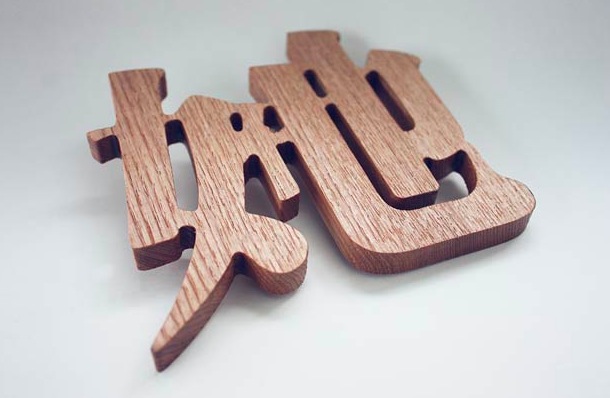
Asiatische Schriftarten haben für mich immer etwas sehr Ästhetisches und irgendwie Beruhigendes. Ich finde man spürt förmlich die lange Tradition der Schriftkunst in den perfekt geschwungenen Linien und Zeichen. Ganz besonders beeindruckend sind natürlich die sehr komplexen chinesischen Schriftzeichen, die auf chinesisch „hànzì“ genannt werden. Bei so viel Schrifttradition und einer Schrift, die aus mehreren tausend Zeichen besteht, ist es natürlich ganz besonders spannend zu beobachten, wie moderne Typografen und Designer die Schriftzeichen in ihren modernen Arbeiten interpretieren.
Die chinesische Kunst- und Designszene stand längere Zeit im Schatten der sehr viel moderneren Designarbeiten aus Japan oder Korea. Doch in den letzten Jahren hat sich einiges getan und in den chinesischen Megacities gibt es heute eine lebendige Szene junger Künstler und Designer. Da es immer wieder spannend ist, sich von Design und Kunst aus anderen Kulturkreisen inspirieren zu lassen, habe ich hier einige typografische Arbeiten aus China zusammen gestellt.
Plakatkunst
Dieses typografische Plakat hat der sehr erfolgreicher junger Grafikdesigner Qian Qian gestaltet. Mir gefällt besonders die Kombination aus modernem, minimalistischem Design und den traditionellen, wie ein Holzschnitt wirkenden Muster. Weitere Arbeiten des Künstlers kannst du dir auch auf seiner Webseite www.q2design.com anschauen.
Piktogramme
Die Piktogramme wurden alle nach bekannten Schriftzeichen, Figuren aus bekannten chinesischen Sagen oder Sprichwörtern gestaltet. Die ursprüngliche Vorgehensweise, chinesische Schriftzeichen von Symbolen herzuleiten: 人 (Lautschrift: ren) ist z.B. das Zeichen für Mensch und sieht aus wie ein laufender Mensch, wurde bei den Piktogrammen also umgekehrt.
Buchstaben aus Holz
Diese Holzbuchstaben für die Zeichen Frau und Mann sind frei interpretierte Eigenkreationen der Shanghaier Künstlerin Moma.
Chinesische Fonts
Die Designagentur REDESIGN hat bereits einige moderne sehr harmonische, chinesische Schriften herausgebracht. Die Schriften können für kommerzielle oder private Projekte auf der Webseite von REDESIGN erworben werden.
Moderne Kalligrafie
Chinesische Kalligrafie hat eine lange Tradition und ist auch in modernen chinesischen Kunst- und Design-Arbeiten meist sehr präsent. Daher finde ich es sehr spannend, sich auch diese Kunstrichtung genauer anzuschauen.
hmmm… irgendwie finde ich die Chinesische Typografie ein wenig eintönig… am besten find ich noch das ausgestochene Holz. Zwar klasse Artikel aber ich bin ehrlich: Irgendwie gefällt mir die Typografie Tradition nicht ganz so wie andere Typografien…
Vincent, als Fremdsprachensetzer fallen mir zu chinesischer Typo unzählige Attribute ein, nur eines nicht: eintönig.
Vielleicht lohnt es sich, sich mal mehr als fünf Minuten mit einer mehrtausendjährigen Tradition zu beschäftigen – nicht, um die Schrift zu lernen, sondern nur, um zu begreifen, welche grundlegende und umfassende Entwicklung hinter diesem Schriftsystem steckt.
Jedesmal, wenn ich ein Magazinlayout ins Chinesische übertragen muß, verhagelt es mir das Design, aber die Vielfalt der Glyphen wiegt das auf. Ich geb’ ihnen sogar schon Namen: „Hutständer“, „Fernsehtisch“, „Stummer Diener“, „Klettergerüst“ etc. etc. – sonst würde ich sie beim Copy&Paste von Korrekturen nicht wiederfinden …
Eintönig … tsts
@Vincent, @muellermanfred,
vielen Dank für eure Kommentare und Einschätzungen zu den Typo-Inspirationen :-) Ja, eintönig ist sicher nicht das richtige Wort, aber die chinesische Schrift ist auch wirklich sehr fremd und es ist sicher nötig, sich etwas mehr mit dem Thema auseinander zu setzen.
Da ich mich in meinem Studium recht intensiv mit chinesischer Schrift beschäftigt habe, würde ich sehr gerne noch ein oder zwei Folgeartikel machen und etwas näher auf die Schrift, ihren Aufbau und auch die Problematiken im Umgang mit Webfonts etc. eingehen.
Schließlich kommt es häufiger vor, dass man auch als Webdesigner mit der Integration verschiedener Sprachen bzw. Schriften konfrontiert wird.
Also ein „follow up“ wird folgen :-)
Wirklich schöne Beispiele! Da gäbe es so vieles, was man zum Thema noch sagen könnte…
Aber in einer Sache möchte ich Dich korrigieren: es handelt sich nicht um „Buchstaben“ aus Holz, sondern um „Schriftzeichen“. Der Unterschied ist, dass es im Chinesischen (noch mehr als im Japanischen) keine Verschriftlichung mithilfe einzelner Zeichen gibt, sondern eine Beschreibung der Sprache mithilfe von Zeichen, die eine oder mehrere Silben repräsentieren. Und, wie Du richtig schreibst, sind viele Zeichen an eine Bedeutung gekoppelt und sind allein deswegen nicht mit Buchstaben gleichzusetzen.